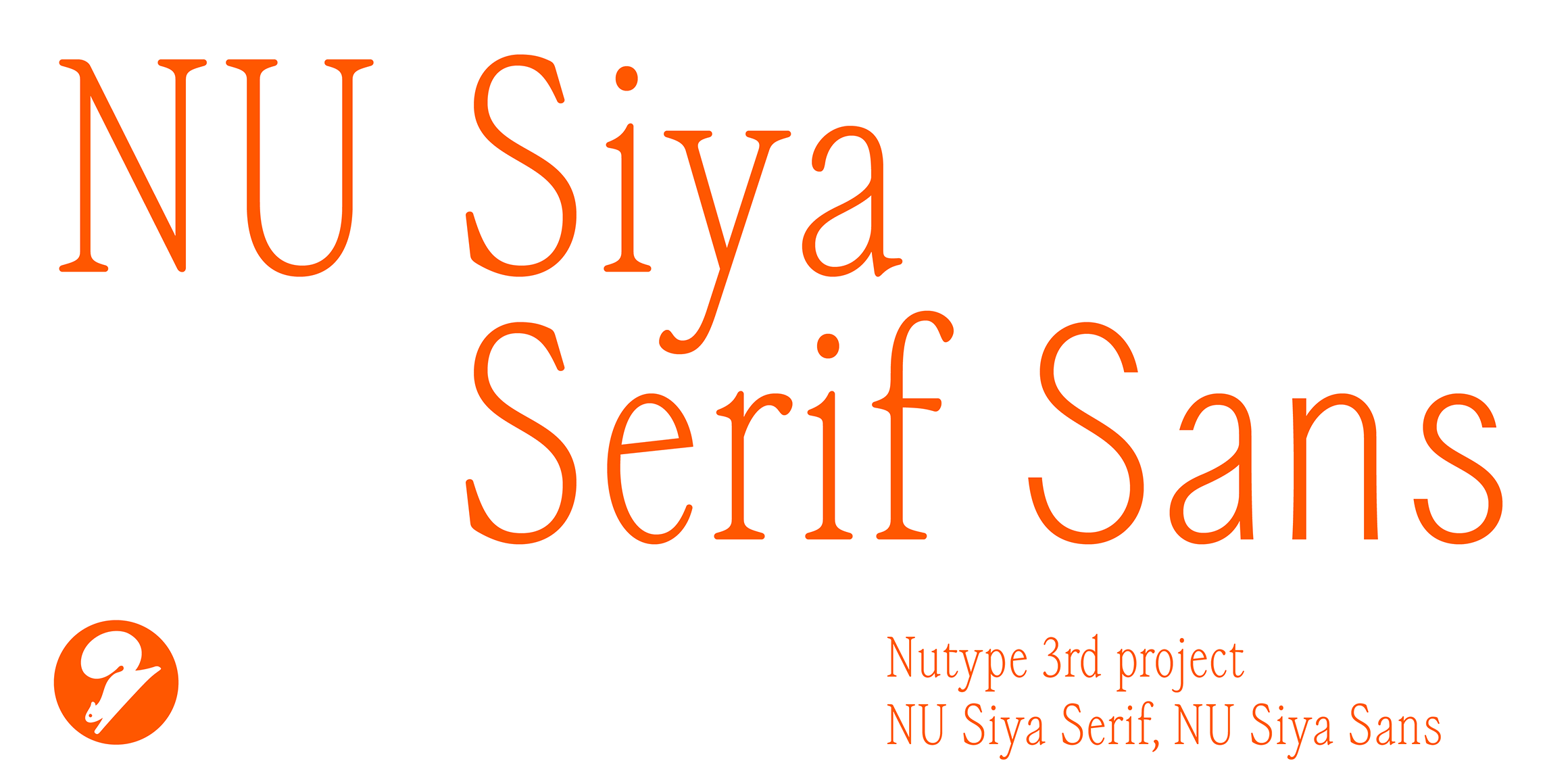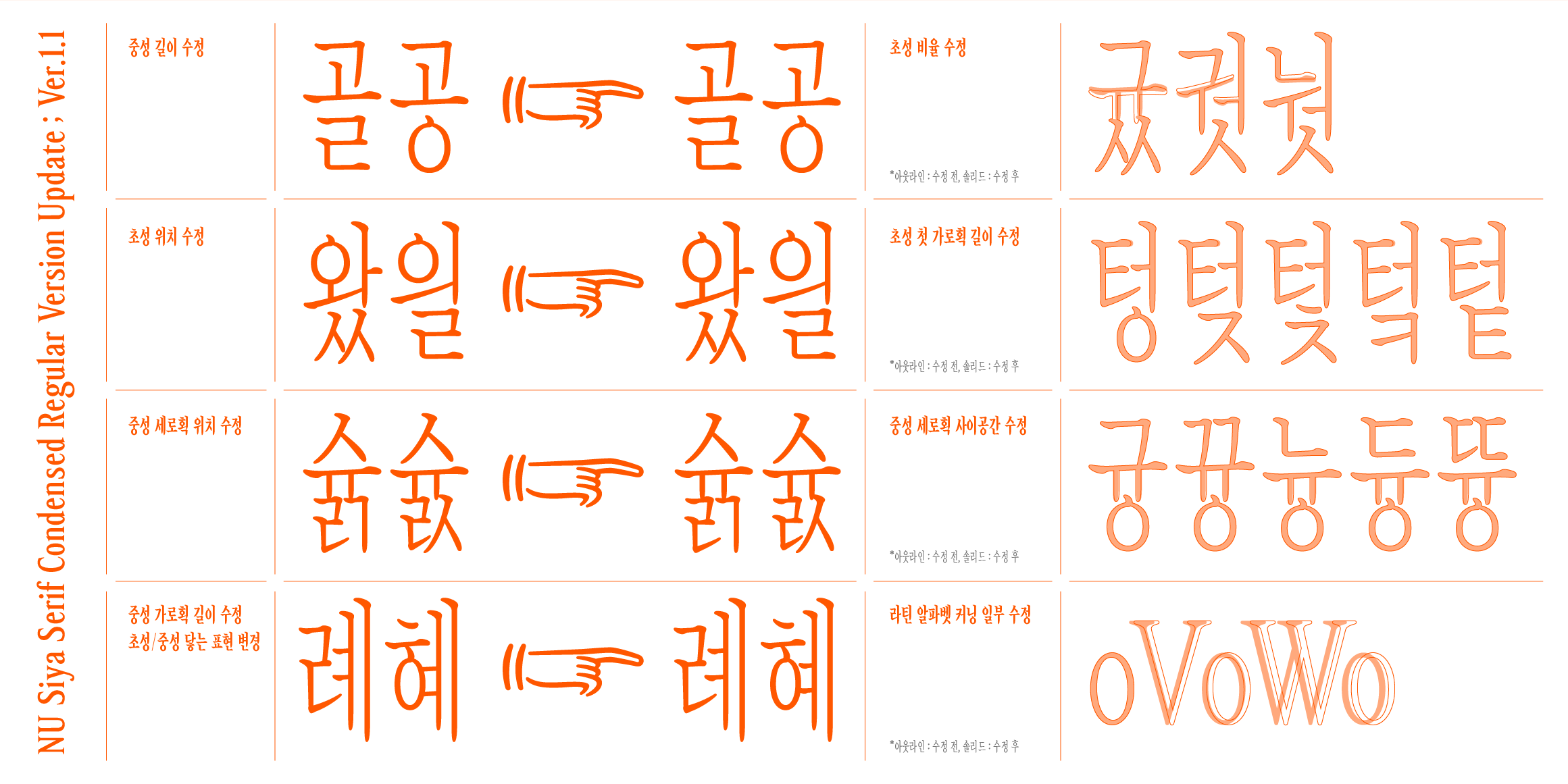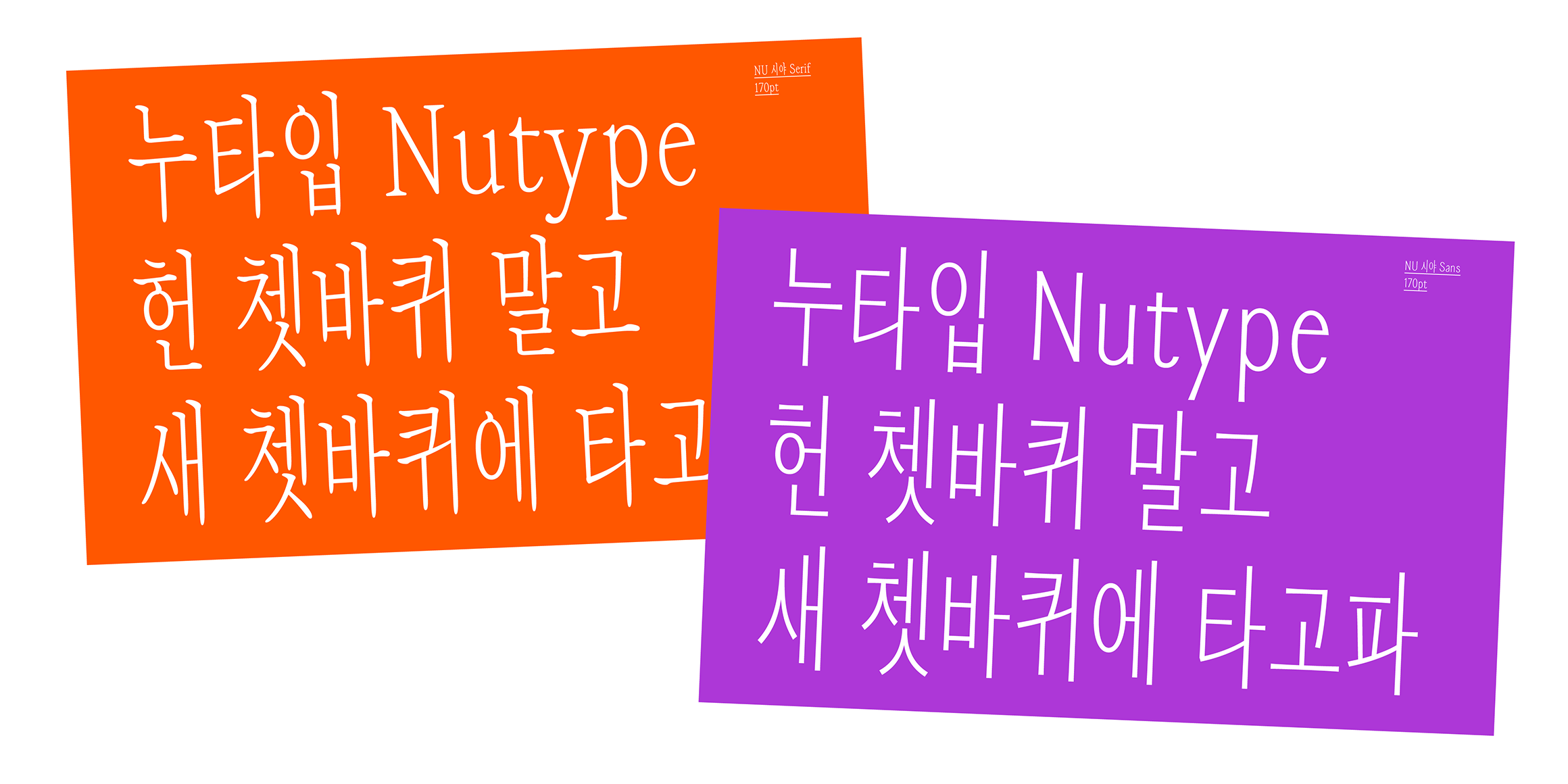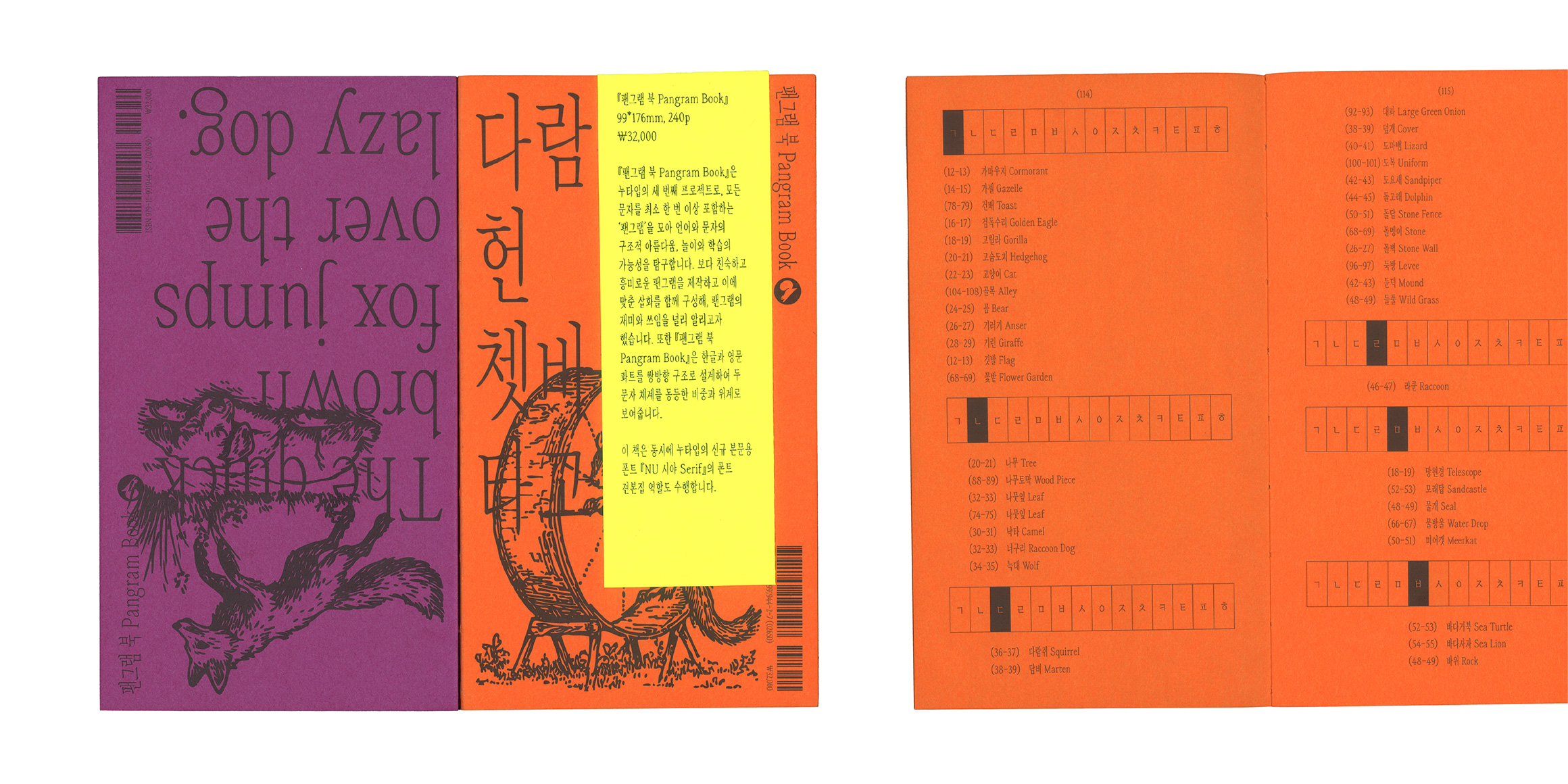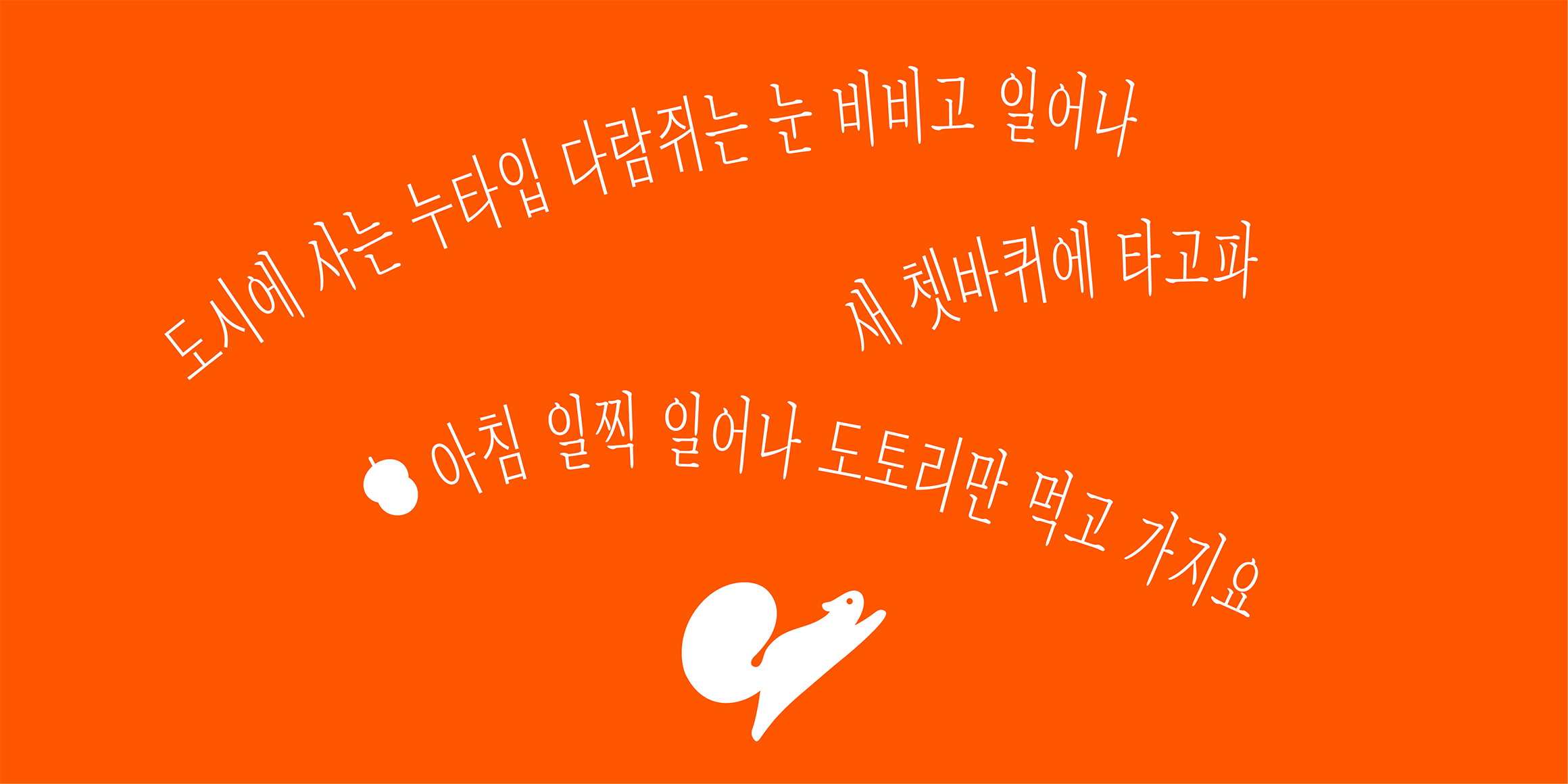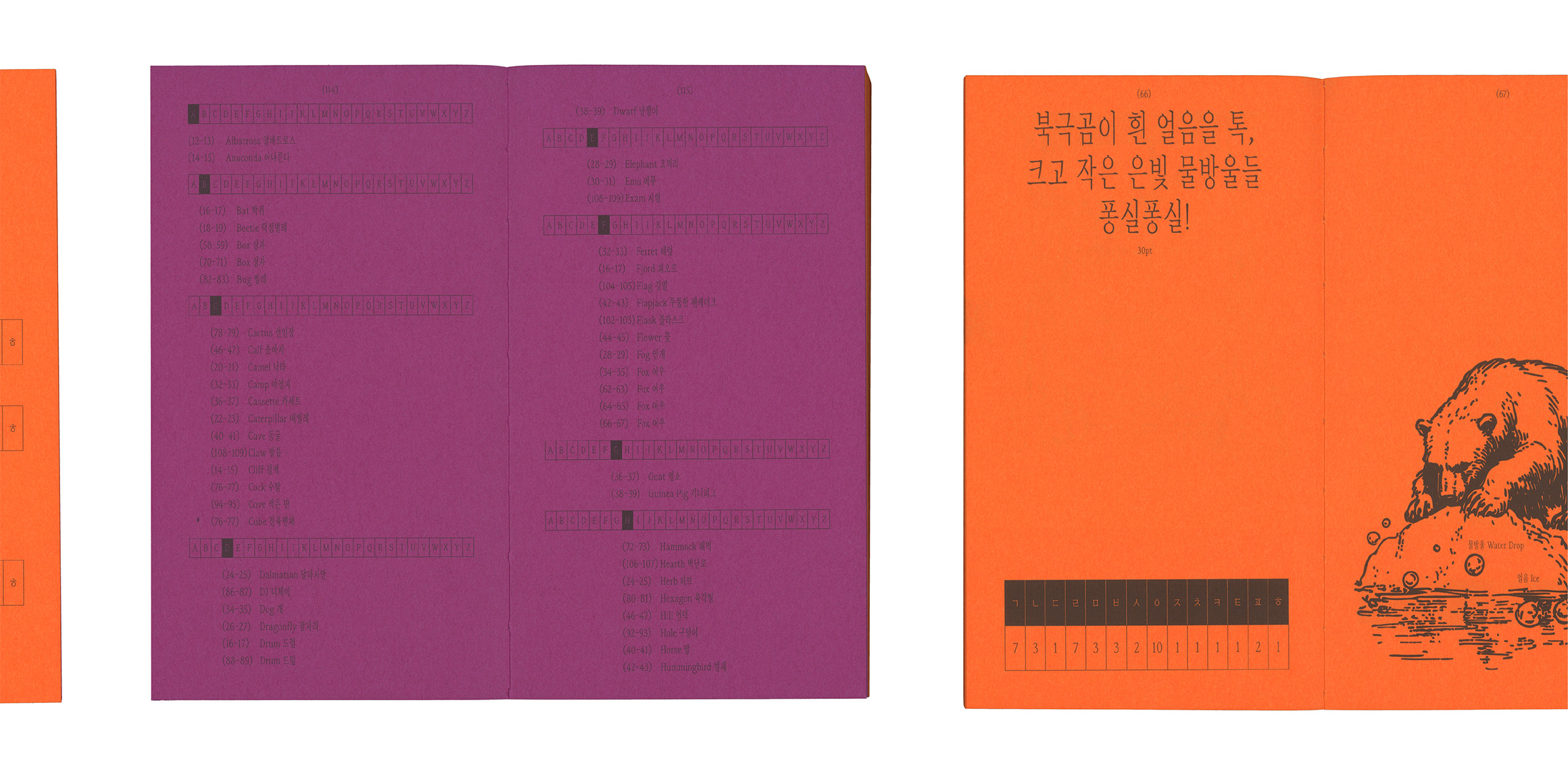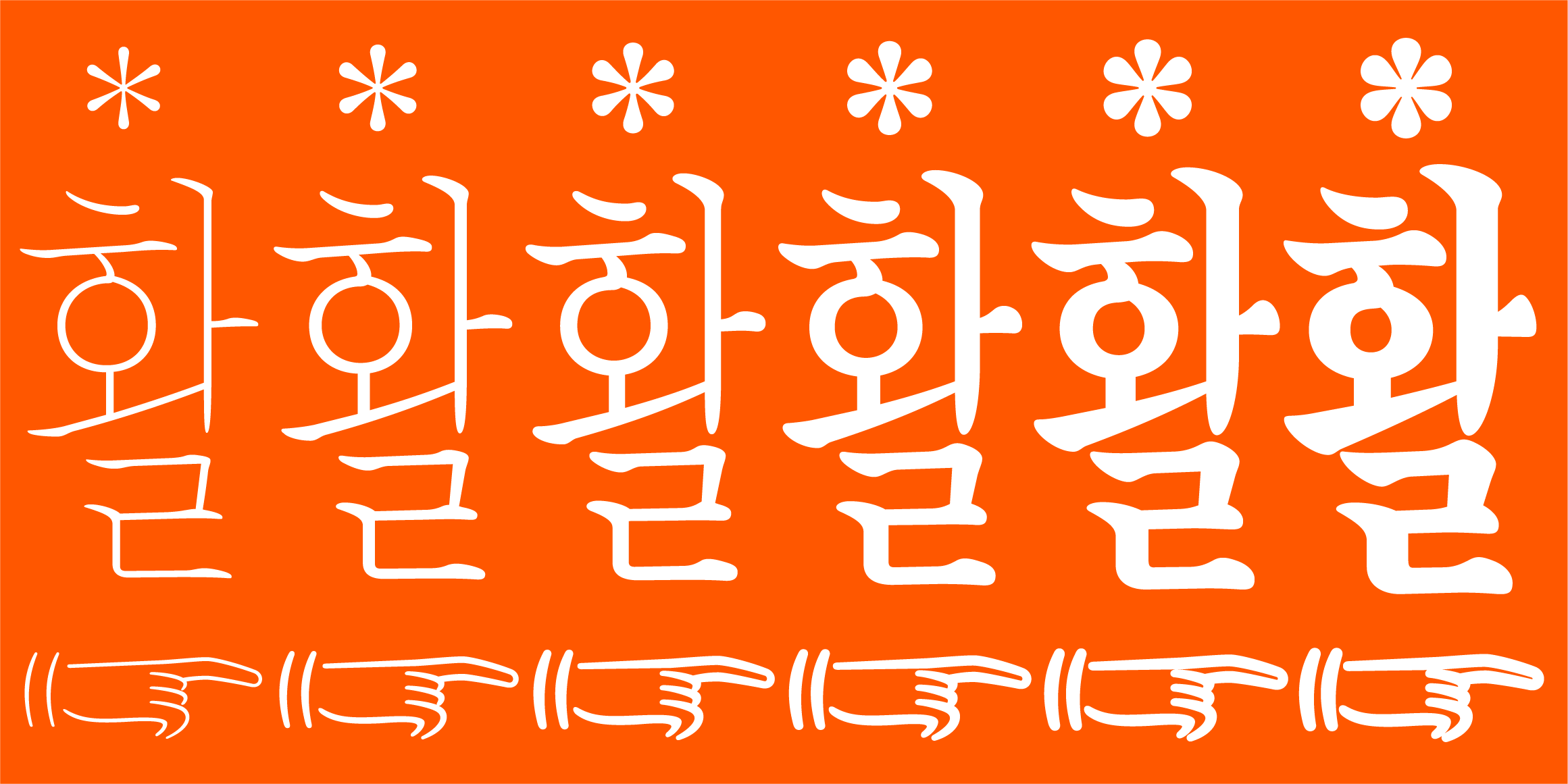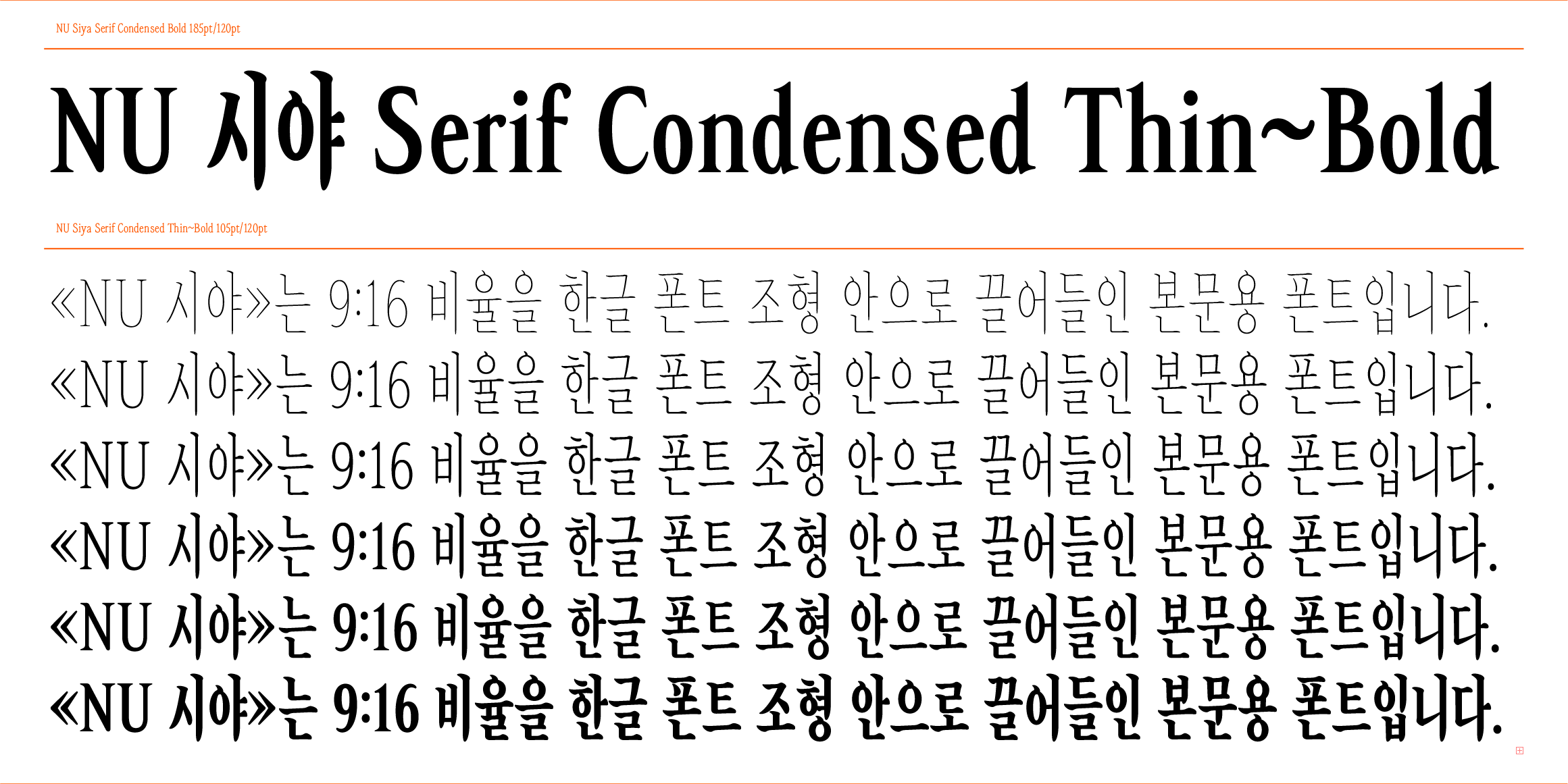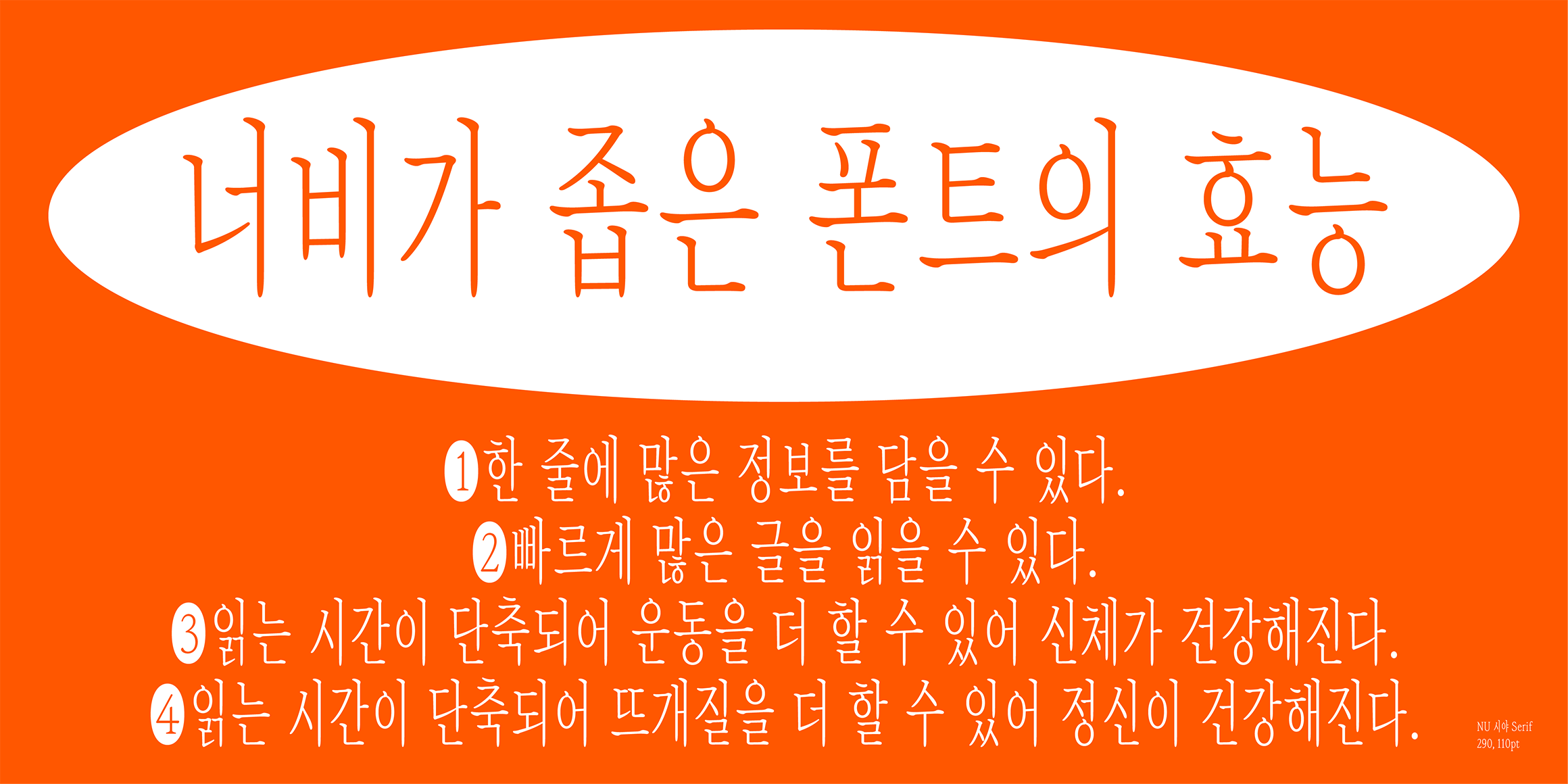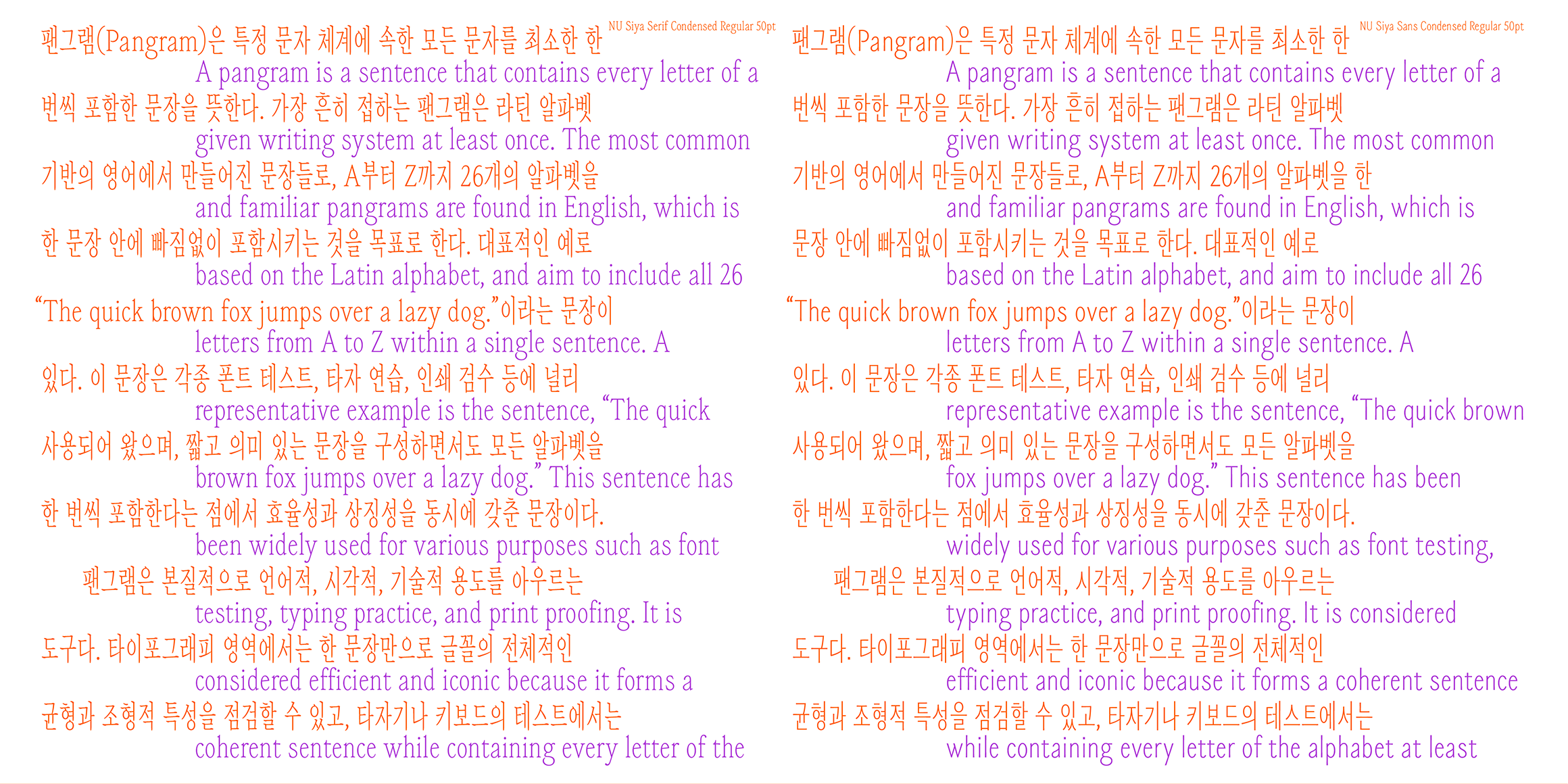
이러한 구조는 디지털 환경에서의 시각적 경험을 반영함과 동시에, 좁은 폭으로 더 많은 정보를 담아낼 수 있는 조형적 밀도를 형성합니다. 특히 세로형 판형과 스크롤 중심의 읽기 방식에서 텍스트가 더 많이, 빠르게 노출될 수 있는 장점을 갖습니다. 이처럼 «NU 시야»는 스크롤 시대의 감각과 정보 밀도의 변화를 타이포그래피 조형에 반영한 폰트입니다.
Serif(6종), Sans(1종)로 구성되어 있으며, Sans의 웨이트는 2026년 5월에 추가될 예정입니다.
00NU 시야